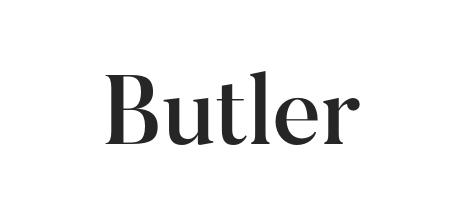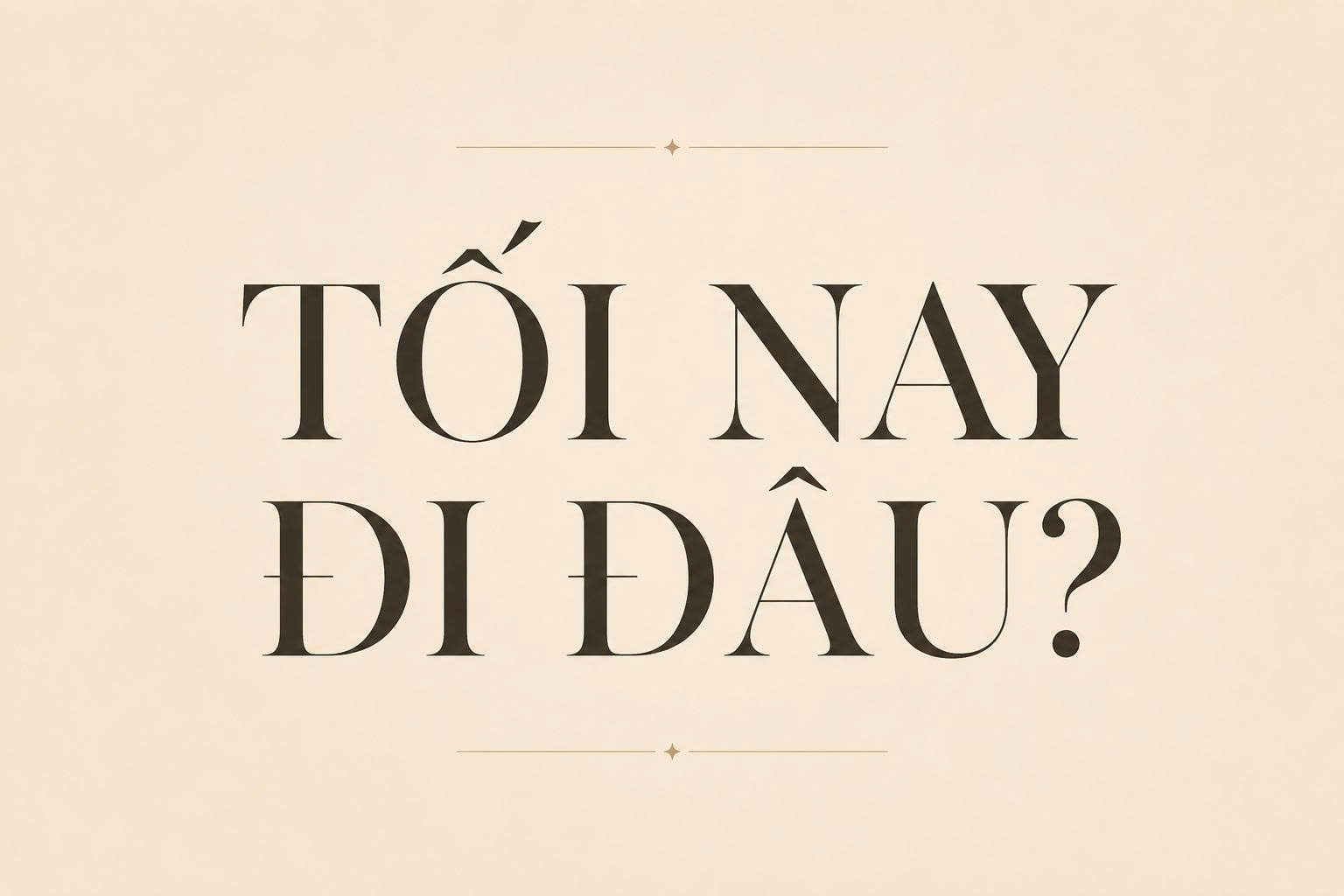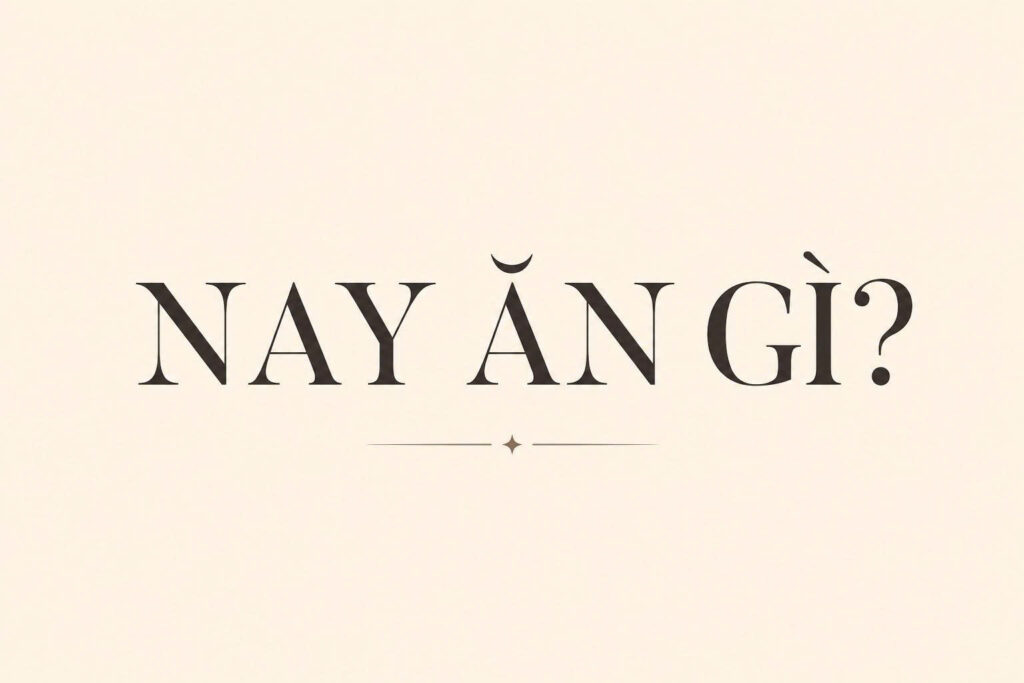
Font Butler Việt hóa là bộ phông chữ thuộc dòng Modern Serif thời thượng do nhà thiết kế Fabian De Smet sáng tạo, lấy cảm hứng từ sự hòa quyện giữa kiểu chữ Dala Floda danh tiếng và cấu trúc hình học chuẩn mực của dòng Bodoni kinh điển. Với các đường nét tương phản sắc sảo giữa nét thanh mảnh và nét đậm đà, font Butler Việt hóa là chất liệu trực quan tuyệt vời để các kiến trúc sư, nhà thiết kế nâng tầm không gian cho các bản vẽ phối cảnh biệt thự nghỉ dưỡng cao cấp, sảnh đón tiếp khách sạn boutique hay bìa hồ sơ năng lực dự án.
Sự giao thoa tân cổ điển và độ tương phản sắc sảo của font Butler Việt hóa
Điểm cuốn hút của font Butler Việt hóa nằm ở cấu trúc hình thể kiêu sa, nơi các đường cong chuyển tiếp mượt mà kết hợp cùng các góc chân chữ (serif) vuốt nhọn dứt khoát, mang lại cảm giác đĩnh đạc và thời thượng của các ấn phẩm tạp chí kiến trúc châu Âu. Độ dày nét được tính toán có độ tương phản cao, giúp các tiêu đề bản vẽ toát lên vẻ ngoài sang trọng và thu hút thị giác từ cái nhìn đầu tiên.
Sự ổn định về mặt thị giác của dòng font này giúp khẳng định vị thế, sự tinh tế và gu thẩm mỹ sắc bén của đơn vị chủ trì dự án. Khi xuất hiện trên các bề mặt vật liệu kiến trúc hiện đại như đá cẩm thạch trắng vân mây, inox mạ vàng xước mờ, kính phản quang hay gỗ óc chó trong các căn nhà lắp ghép cao cấp, Butler tạo nên điểm nhấn thị giác cuốn hút.
| Phân loại phong cách | Modern Serif / High-contrast / Editorial Display |
| Hệ thống biến thể | 14 kiểu (7 cấp độ nét thường & 7 cấp độ Stencil) |
| Mục đích phù hợp | Biển tên villa cao cấp, bìa hồ sơ năng lực, logo |
Tư vấn từ chuyên viên: Butler sở hữu các nét thanh mảnh và độ tương phản lớn. Để bản thiết kế đạt hiệu quả thẩm mỹ tốt, bạn nên sử dụng phông chữ này cho các tiêu đề chính, tên dự án hoặc câu slogan ngắn ở kích thước lớn từ 18pt trở lên.
03 Ứng dụng phông chữ Butler vào công trình thực tế
Nhờ vẻ ngoài quý phái và tính thẩm mỹ cao cấp, bộ phông chữ này mang lại giá trị thực tế lớn trong khâu tạo điểm nhấn cho các công trình hiện đại:
- Biển hiệu mặt tiền cho Showroom Nội thất và Villa Nghỉ dưỡng: Những nét chữ thanh lịch của Butler rất ăn ý khi gia công chữ nổi bằng inox vàng gương hoặc khắc chìm trên đá hoa cương, giúp căn nhà lắp ghép toát lên vẻ đài các và thu hút sự chú ý của du khách.
- Bìa hồ sơ năng lực dự án kiến trúc: Sử dụng font Butler Việt hóa cho tên dự án và tiêu đề các chương mục giúp hồ sơ trông như một ấn phẩm tạp chí danh giá, thể hiện gu thẩm mỹ tinh tế và năng lực của đơn vị kiến tạo.
- Hệ thống biển tên phòng và bảng chỉ dẫn nội khu: Phông chữ này khi in trên kính mờ hoặc kim loại phủ sơn tĩnh điện sẽ giúp không gian sảnh đón tiếp và hành lang toát lên chất nghệ thuật thanh lịch.
03 Lưu ý bố cục font Butler Việt hóa luôn sang trọng và tinh tế
Để khai thác hiệu quả vẻ đẹp của dòng font thời trang quý tộc này mà không làm ảnh hưởng đến khả năng đọc của bản vẽ, người thiết kế nên lưu tâm một số kinh nghiệm sau:
- Tránh sử dụng ở kích thước quá nhỏ: Do có các nét thanh mảnh như sợi chỉ, Butler hiển thị đẹp ở kích thước chữ từ trung bình trở lên trong in ấn. Ở kích thước quá nhỏ, nét thanh có thể bị mờ nhòe do độ mịn của chất liệu giấy in.
- Nới rộng khoảng cách ký tự: Đối với các tiêu đề viết hoa toàn bộ, việc kéo giãn nhẹ khoảng cách giữa các chữ cái sẽ làm tăng tính trang nghiêm, giúp bố cục thông thoáng và mang đậm phong thái kiến trúc đương đại.
- Bố trí nền màu đơn sắc tương phản: Butler phát huy hiệu quả thị giác cao khi đặt trên các nền màu đơn sắc có chiều sâu như đen tuyền, trắng ngọc trai, xám than hoặc xanh rêu sẫm, giúp các đường nét sắc sảo của bộ chữ được tôn vinh rõ ràng.